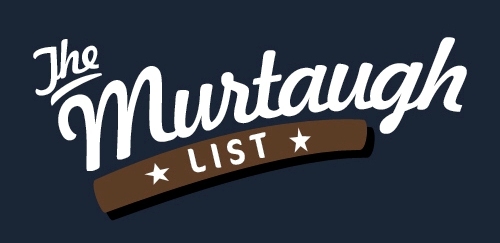
Hallo, ich suche den Namen zur Schriftart in folgendem Bild.
Gemeint ist die große Schrift auf blauem Grund. Gern nehm ich auch eine die dieser sehr nahe kommt. Danke schonmal.
ähnelt „Brush Script“ - ist es aber nicht.
Sie sieht so aus, wie diese unsägliche Schriftart, die scheinbar vom Gesetz für die Namensschilder amerikanischer Angesteller vorgeschrieben ist.